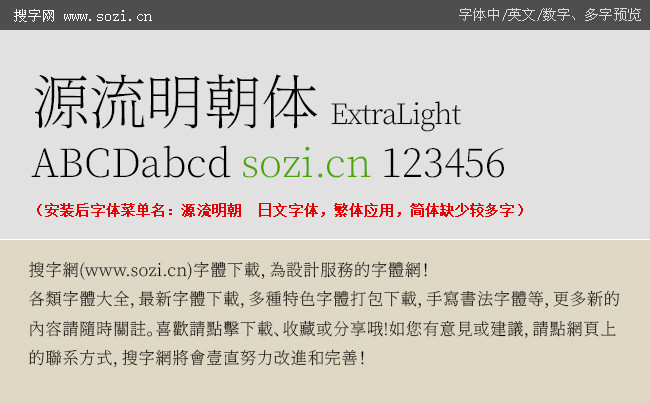
源流明朝ExtraLight
搜字網(wǎng)給大家提供一款源流明朝ExtraLight中文字體下載,源流明朝體源自思源宋體,風(fēng)格較原字體改變較大,尤其是勾的筆畫更加具有線條感,使字型看起來更有力道。漢字寬度稍微壓縮,顯得比原始的思源宋體要稍微瘦長(zhǎng)。并且在橫筆的起筆與豎筆的起筆、收筆,全都加上粗細(xì)變化,仿佛重現(xiàn)鉛字的壓印感,文字較有文學(xué)感、人文氣息。適用于大標(biāo)題、包裝設(shè)計(jì)、海報(bào)設(shè)計(jì)等應(yīng)用。